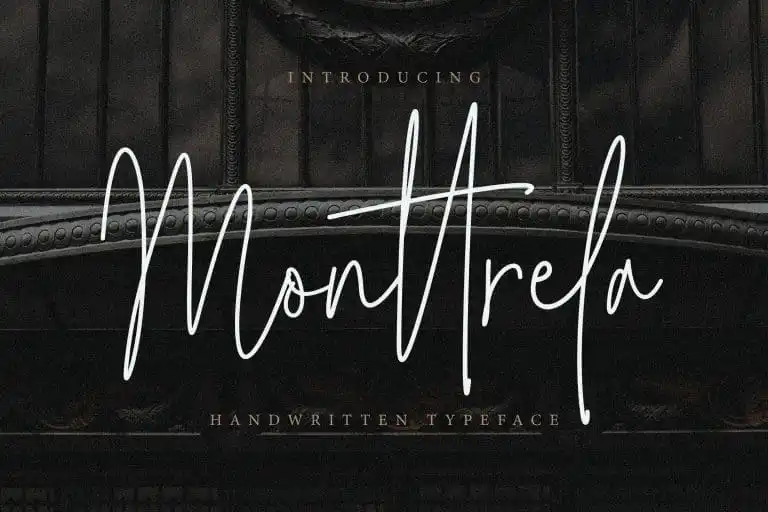
A Monttrela Signature Font é uma elegante tipografia script que transmite ao mesmo tempo elegância e modernidade. Desenhada e compartilhada pela Creatype Studio, essa fonte atingiu um nível de sofisticação impressionante, tornando-se perfeita para design de cartões casamento, cartas de agradecimento, citações, cartões de saudação, logotipos, cartões de visita e qualquer outro projeto gráfico que precise de uma pitada de escrita manual. Suavemente delicada e modernamente sofisticada, essa fonte impressionante brilha em diversos projetos, tornando a Monttrela Signature Font um recurso indispensável para designers e criativos do Brasil.